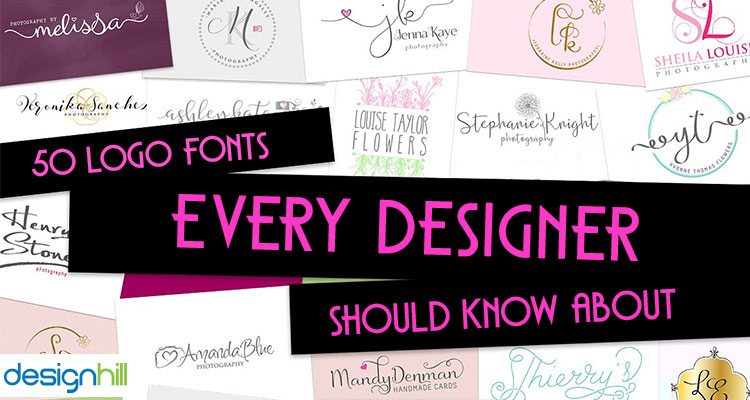
25 Font Logo yang Harus Diketahui Setiap Desainer
‘Jenis desain adalah tentang fungsi. Menggambar bentuk yang bagus saja tidak cukup. ‘ – James Todd
Seringkali kita memikirkan warna dan gambar dalam desain grafis, terutama dalam logo. Tetapi font logo adalah elemen desain yang sama pentingnya. Bahkan, banyak logo perusahaan ikonik berbasis tipografi. Jika logo memiliki nama bisnis, keberhasilan desainnya tergantung pada penggunaan font yang terampil. Untungnya, beragam font dapat diakses untuk membuat pilihan yang benar.
Hanya seorang desainer grafis yang terlatih dan berpengalaman yang dapat memasukkan font sempurna seperti itu dalam desain. Seorang desainer yang terampil memahami bagaimana memberikan bentuk yang berbeda pada jenis huruf konvensional dapat membuat desain yang unik. Sebagai contoh, banyak logo telah memberikan tampilan baru pada huruf-huruf klasik. Logo Coca-Cola adalah salah satu contoh cemerlang tentang bagaimana huruf dapat menciptakan identitas merek. Menurut entrepreneur.com, tipografi yang kuat adalah salah satu tips kunci untuk desain logo pemenang penghargaan. Ini terutama karena jenis huruf itu sendiri berfungsi sebagai visual.
Jadi, apakah logo bisnis Anda berdasarkan tipografi? Jika ya, maka lihat dan cari tahu apakah itu benar menggunakan kekuatan jenis huruf. Pastikan font yang digunakan dalam logo perusahaan Anda sinkron dengan kepribadian merek Anda.
Font yang bagus membuat semua perbedaan! Font logo Anda memainkan peran penting dalam membentuk citra bisnis Anda. Percaya atau tidak, jenis huruf logo Anda bercerita tentang logo merek Anda sebelum kata-kata itu muncul. Dan pilihan font Anda dapat membuat atau menghancurkan desain logo Anda.
Tetapi dengan begitu banyak font di web pada platform yang berbeda, mungkin sulit bagi seorang desainer untuk memilih satu font untuk logo. Namun, ada beberapa font yang harus dimiliki para desainer dalam koleksi mereka untuk membuat kesan pertama!
Inilah Daftar 25 Font Logo Yang Harus Diketahui Setiap Desainer
01. Garamond
Ini bukan font tunggal tetapi keluarga tipografi serif lama. Font ini memiliki keterbacaan yang sangat baik dan elegan. Jenis huruf yang berbeda termasuk Adobe Garamond, Stempel Garamond, EB Garamond, Sabon Next dan ITC Garamond. Ini biasanya digunakan oleh majalah, situs web, buku teks dan teks panjang. Sebuah publikasi Jerman telah menilai jenis huruf ini sebagai yang terbaik kedua di antara semua font. Font ini pertama kali dirilis pada tahun 1989.
02. Helvetica
Helvetica adalah salah satu font yang paling banyak digunakan dalam berbagai desain grafis. Profesional sangat menyukai font ini. Helvetica telah dibundel dalam komputer pribadi sejak 1984 dan ini adalah salah satu alasan mengapa Helvetica begitu populer. Banyak profesional suka dan tidak suka jenis huruf ini karena alasan sederhana bahwa huruf-huruf dalam font ini terlalu sempit. Namun, pemilihan font yang cermat diperlukan untuk desain logo yang efektif. Font ini tidak dapat digunakan di mana-mana untuk menyampaikan pesan yang dimaksud.
03. Trajan
Trajan telah lama digunakan dalam poster film Hollywood. Jenis huruf juga merupakan favorit panas bagi banyak desainer yang perlu membuat desain yang berkaitan dengan hukum, pernikahan, agama dan hal-hal tentang masa lalu. Trajan adalah jenis huruf serif gaya lama dan dirancang oleh Carol Twombly pada tahun 1989. Desain jenis huruf ini didasarkan pada ibu kota Romawi. Font ini akan memastikan keserbagunaan desain logo Anda.
04. Futura
Futura dikenal karena lingkaran, kotak, dan segitiga yang nyaris sempurna karena didasarkan pada bentuk geometris. Karena bentuk geometrisnya yang unik, tampilan besar, desain perusahaan, buku, dan logo sering menggunakan font ini. Font dianggap oleh banyak orang sebagai yang ideal untuk teks kecil.
05. Bodoni
Jika Anda mencari jenis huruf yang ideal untuk tajuk utama, logo, dan teks dekoratif, maka Bodoni bisa menjadi taruhan terbaik Anda. Ini memiliki serif datar dan un-kurung dan memiliki struktur dasar yang sempit. Ada sapuan tebal dan tipis di font ini dan ada perbedaan antara keduanya. Font ini terlihat estetis karena konstruksi geometrisnya. Pastikan bahwa Anda menyebutkan font ini terutama di brief desain Anda ketika crowdsourcing pekerjaan desain Anda.
06. Zorus Serif
Zorus Serif diciptakan oleh Jeremie Dupuis, seorang desainer Kanada. Mesin terbang antik font ini memberikan nuansa Gallic yang berbeda. Font ini cocok ketika Anda ingin memberikan kesan cetak dan gaya kuno pada desain Anda. Anda dapat mengakses font ini dalam versi miring dan standar.
07. Sabo
Anda dapat dengan aman mencoba font retro Sabo jika desain Anda memiliki tema arcade. Font ini adalah kreasi desainer grafis Philippe Moesch dan memiliki sistem font gaya piksel yang tidak pernah gagal untuk mengesankan serangan dengan gaya kuno yang mengesankan. Font tersedia dalam dua gaya – diisi dan inline.
08. Bobbers
Bobber adalah serab pelat. Sepeda motor bobber adalah inspirasi di balik penciptaannya. Jika Anda mencari font unik untuk mengekspresikan emosi zaman dulu, maka jenis huruf ini cocok dengan tagihan Anda dengan desain vintage dan kerennya. Ini adalah font berbasis grid yang bebas digunakan untuk tujuan komersial dan pribadi. Pilih font ini jika Anda ingin memiliki desain berbasis tipe yang unik. Font ini dirancang oleh Lucas Almeida dan Dmitry Goloub.